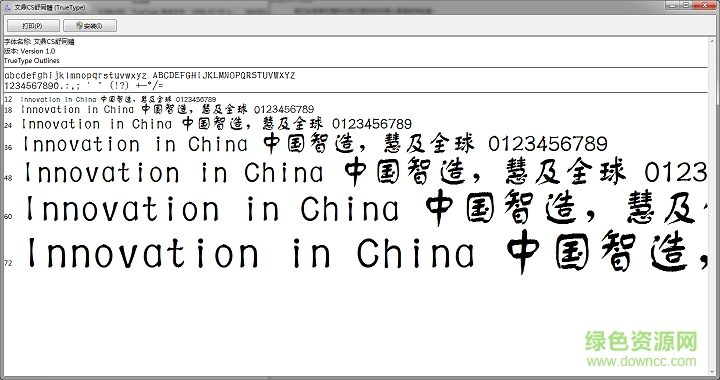
shutonticseg bold gb字體是一款有點(diǎn)像行楷字體的文鼎cs舒同體,筆畫(huà)柔軟流暢,結(jié)體勻稱(chēng),粗細(xì)適中,看上去非常舒服,是書(shū)法家們?cè)跁?shū)寫(xiě)文章中所常用的一種字體類(lèi)型,生活中也比較常見(jiàn),有需要者歡迎來(lái)綠色資源網(wǎng)免費(fèi)下載!